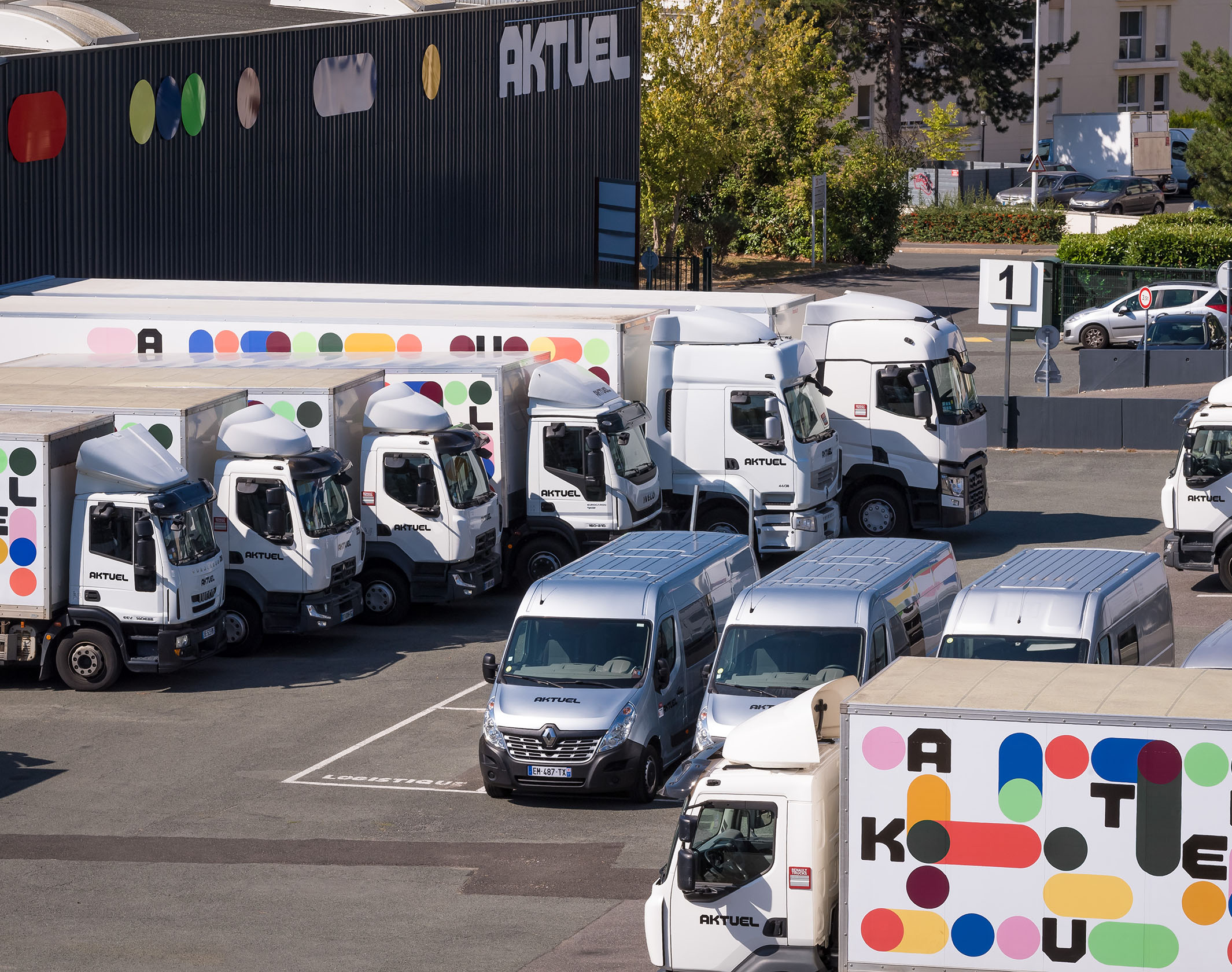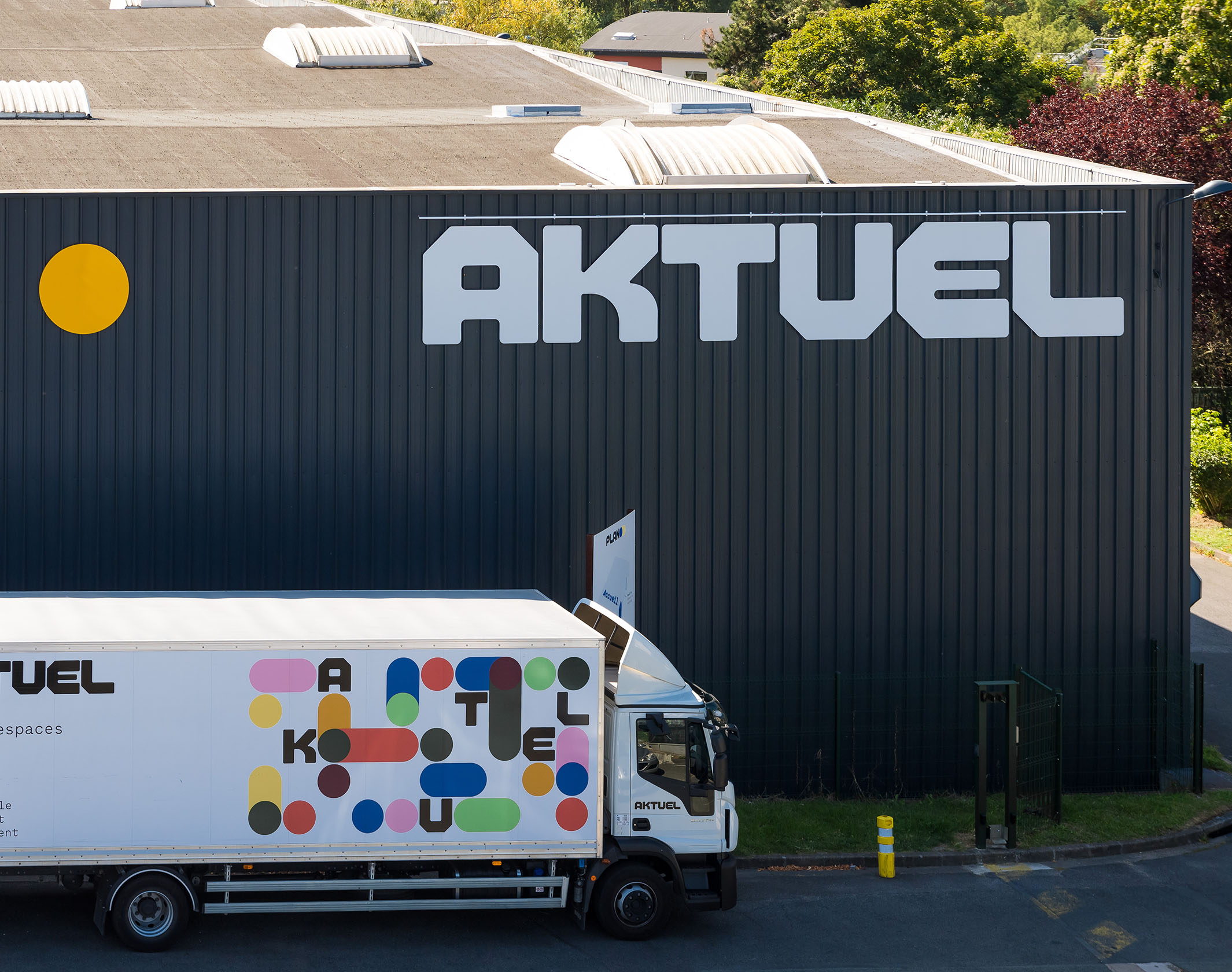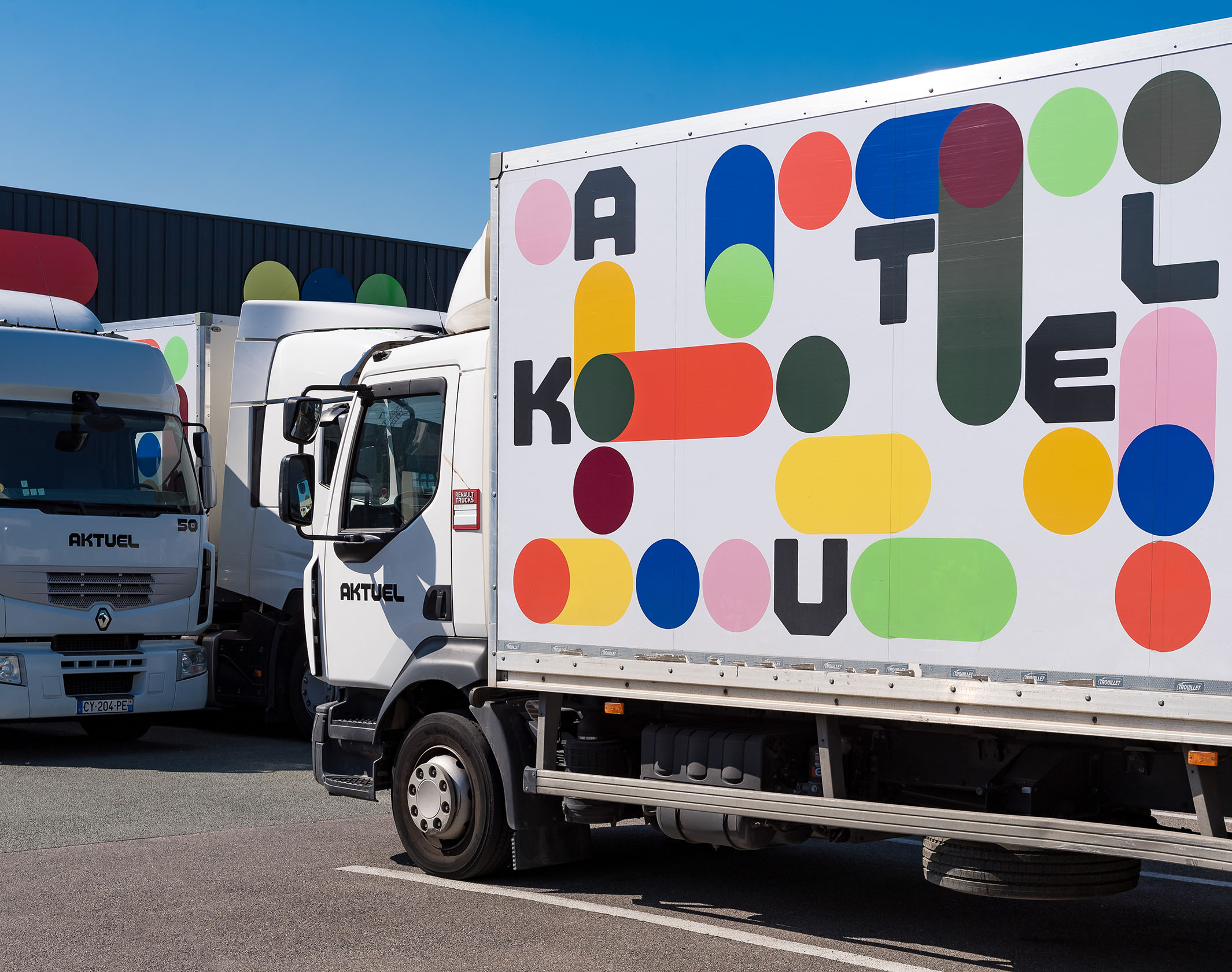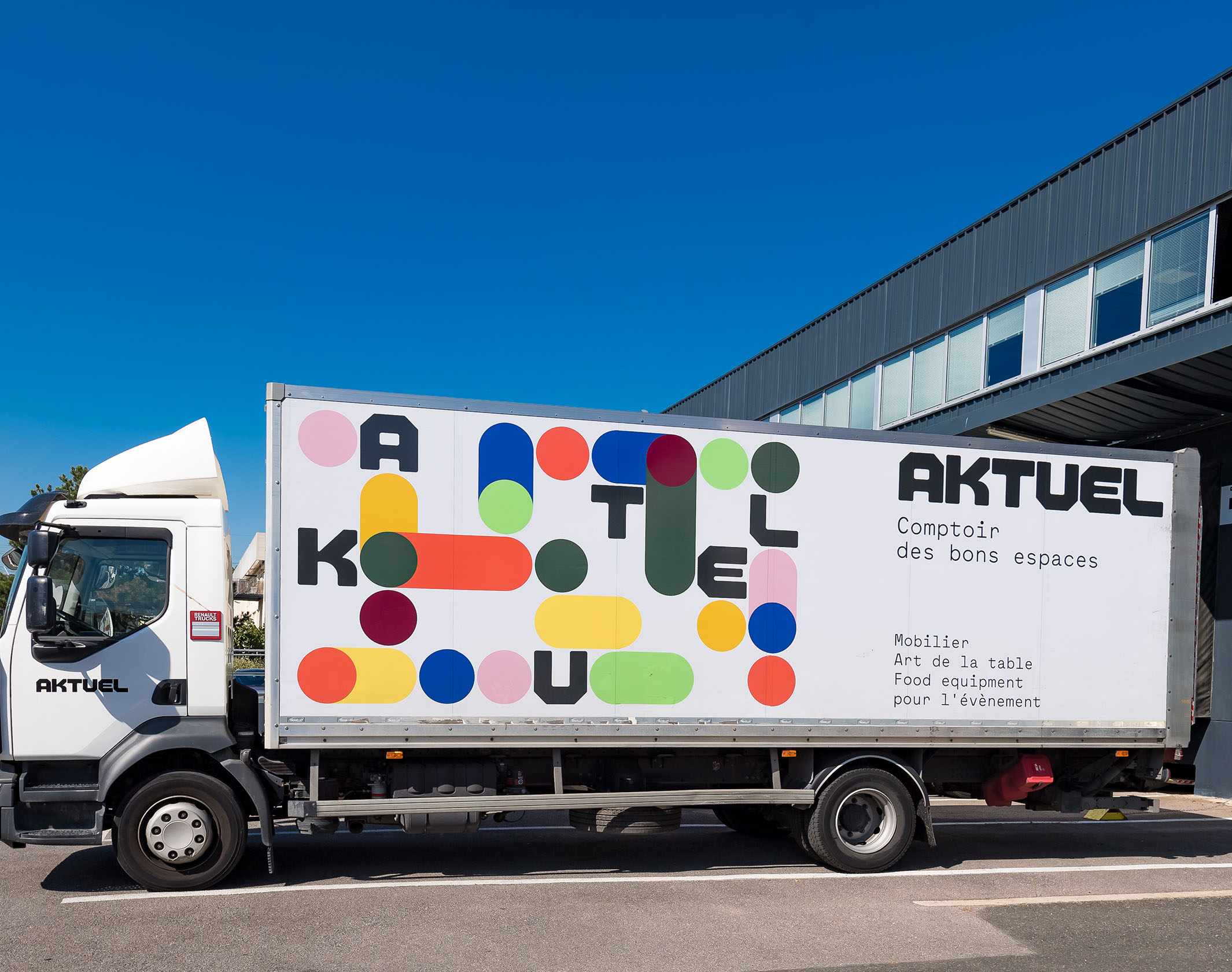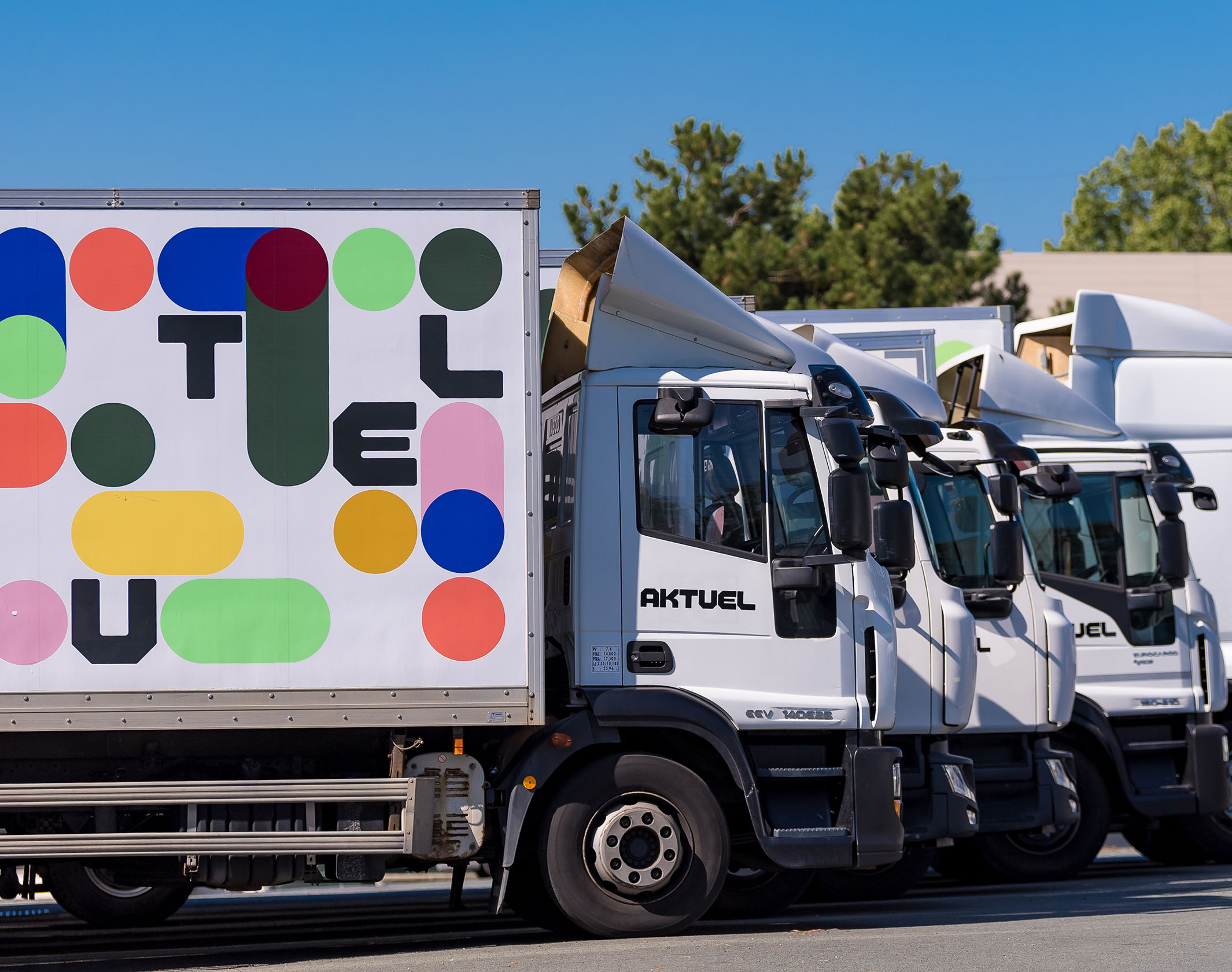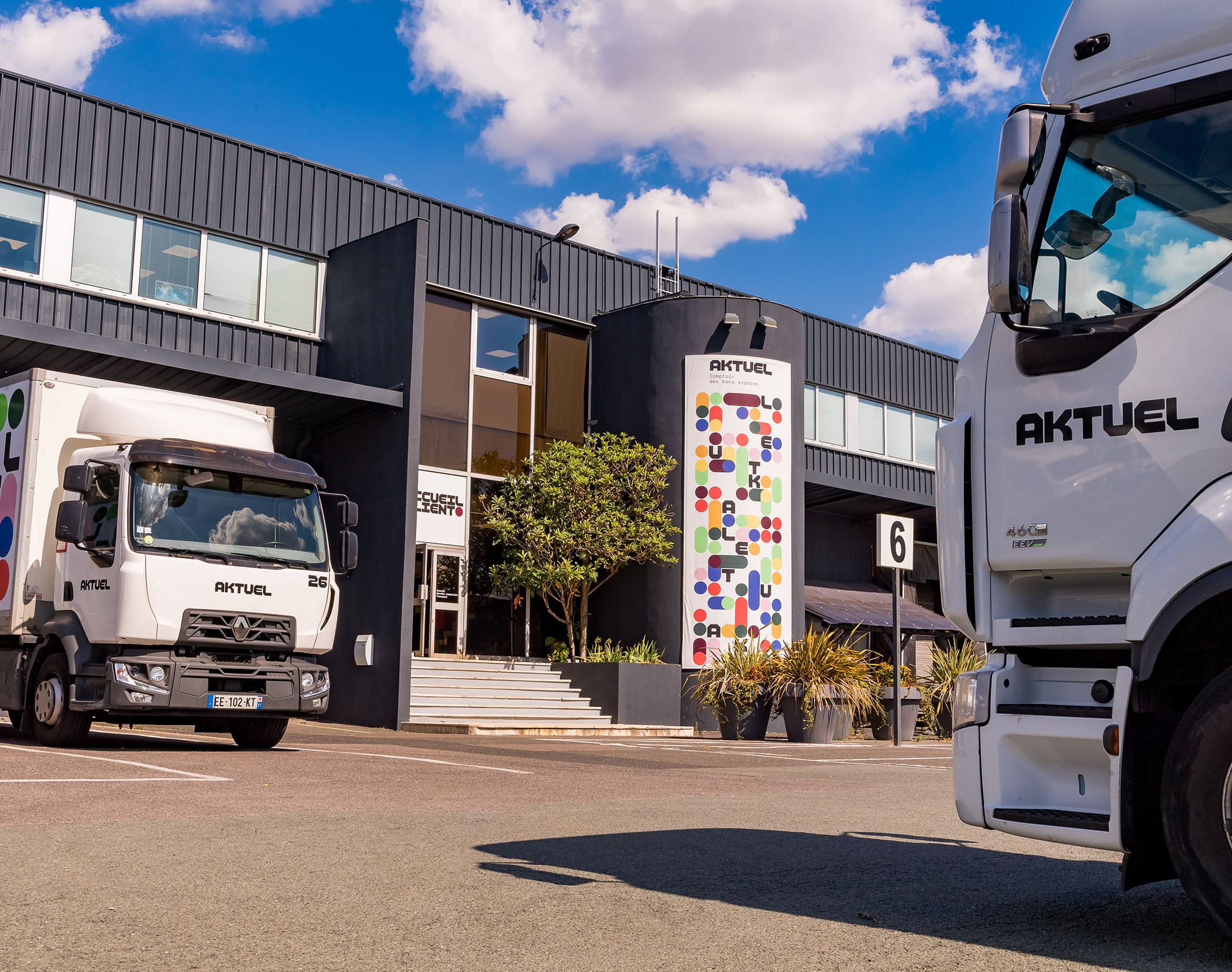
Aktuel
Comptoir des bons espaces
Depuis 1988, Aktuel s’est positionné comme un des acteurs incontournables de la location de mobilier, art de la table et food equipment pour l’événement. Les chiffres : 140 collaborateurs, 3 implantations, 20 000m² de stock, 60 véhicules de livraison, et un nombre incalculable d’événenements équipés, des conventions d’entreprises aux plus grands salons, en passant par les événements sportifs majeurs. Mais surtout, Aktuel revendique à juste titre, au-delà de son métier de logisticien, une approche humaine, simple et pragmatique, louée par l’ensemble de ses clients depuis 30 ans. Un « bureau » composé de gens solides, fiables et impliqués, une relation de travail agréable, et des projets toujours réussis.
Nous avons travaillé au repositionnement stratégique du groupe, pour aboutir à une nouvelle signature – Comptoir des bons espaces – et une traduction graphique au travers d’une nouvelle identité visuelle.
Notre travail de design s’est articulé autour de deux idées : parler du métier historique d’aménageur d’espaces tout en développant la nouvelle vision stratégique mise sur pied lors du travail de positionnement. Trois éléments majeurs composent l’identité graphique : une grille, une typographie dédiée et un ensemble de formes. Le nouveau logo, un typogramme dessiné pour la marque, solide et stable, se décline en une nouvelle police de titrage complète qui forme l’ossature typographique du nouveau branding. Un pattern coloré, modulable à l’infini, vient se greffer à ce socle typographique.
De la papeterie aux objets dérivés, en passant par la flotte de poids lourds et l’application de la nouvelle identité sur le stand de la marque au salon Heavent 2018, où le nouveau branding a été inauguré, nous avons développé un système riche et souple, encapsulant à la fois les notions de rigueur et d’empathie, et qui pose un style distinctif dans le monde de l’événementiel.